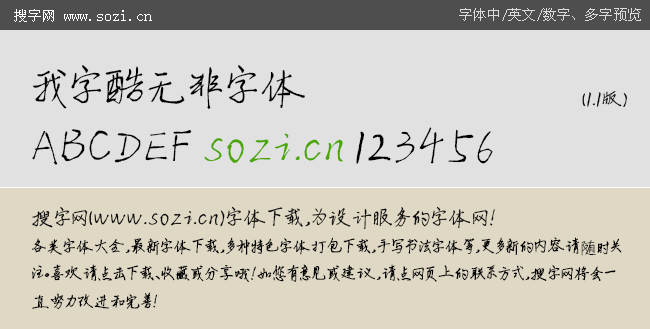
我字酷無非字體
搜字網(wǎng)提供一款我字酷無非字體中文書法字體下載,我字酷無非字體是一款手寫風(fēng)格的鋼筆書法字體,字體書寫流暢,字形大方,整體效果十分出色,適合應(yīng)用于廣告設(shè)計(jì)、名片設(shè)計(jì)、包裝印刷、產(chǎn)品設(shè)計(jì)等應(yīng)用。